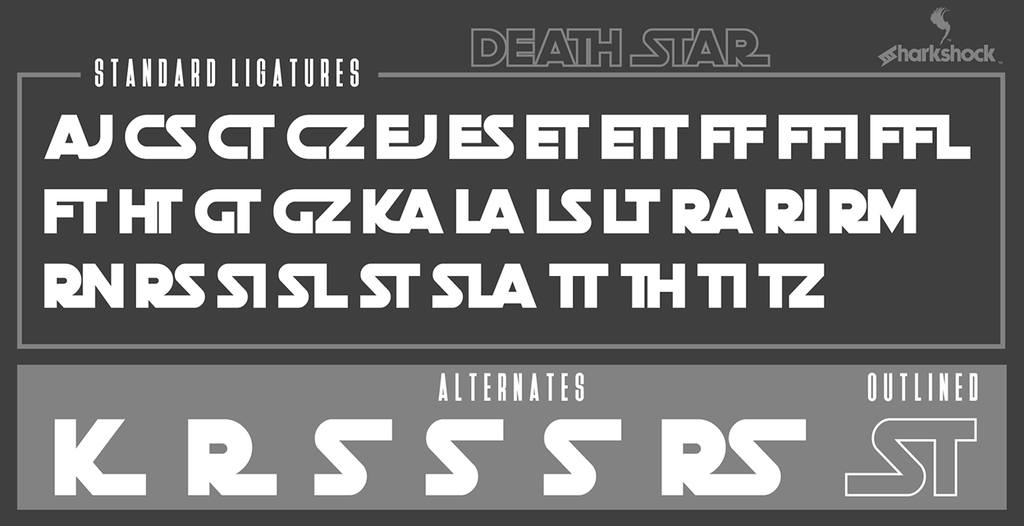
10 ausgezeichnete STEM- und Science-Fonts
Veröffentlicht: 2019-08-09Egal, ob ein Kunde ein retro-futuristisches Design für seine neue Website wünscht, eine Organisation für eine MINT-Veranstaltung in ihrer lokalen Gemeinde wirbt, ein Science-Fiction-Autor ein elegantes Buchcover verlangt oder ein neues Forschungsunternehmen eine hochmoderne Website benötigt, um ihrer Spitzenforschung entsprechen, vermitteln MINT- und Wissenschaftsschriften leicht ein Gefühl von Modernität, klarem Styling und Hightech-Know-how. Mit jedem Eintrag in dieser Liste können Sie das perfekte Design zusammenstellen, in dem sich die Leser wie zu Hause fühlen. Auch wenn sich dieses Zuhause in einer weit, weit entfernten Galaxie befindet.
1. TR2N
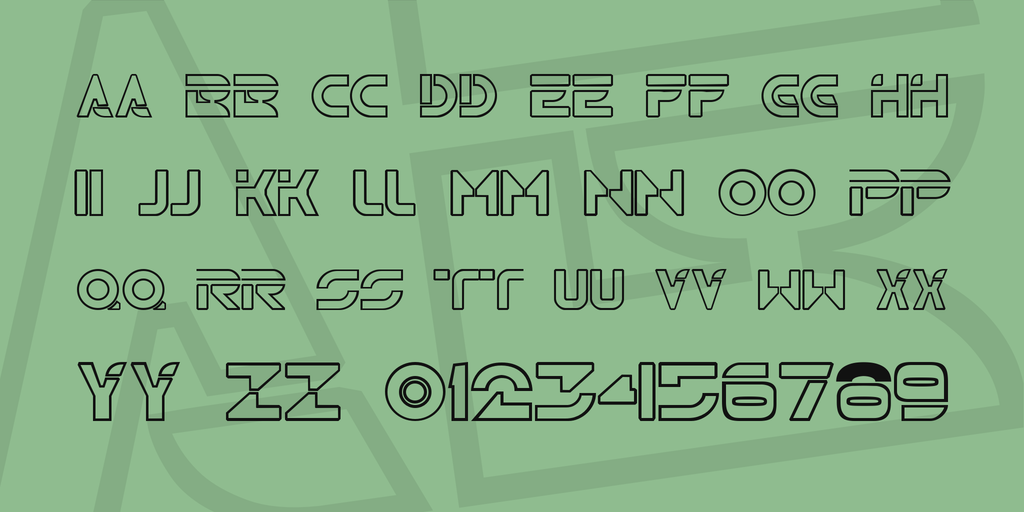
TR2N erinnert an den Disney-Kultklassiker Tron . Diese Schriftart ist eine reine Großbuchstaben-und-Zahlen-Schrift, die nicht für lange Dokumente, sondern für Überschriften und aufmerksamkeitsstarke Designarbeiten entwickelt wurde. Die Schriftart ist gut gemacht und lesbar (für das, was sie ist), ist jedoch stilisiert, sodass Sie dies im Hinterkopf behalten müssen. Wenn es jedoch um Science-Fonts geht (nun, Science-Fiction-Schriften), können Sie nicht viel stärker als TR2N werden. Das Beste daran ist, dass die Schriftart für die kommerzielle Nutzung kostenlos ist, sodass Sie sich in dieser Hinsicht um nichts kümmern müssen.
2. Wissenschaft
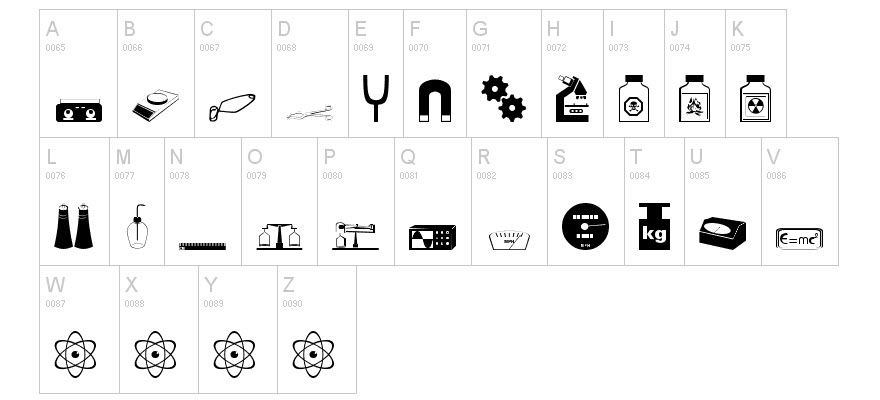
Die passend benannte Science- Schrift ist nicht etwas, mit dem Sie schreiben. Stattdessen handelt es sich um eine Symbolschrift. Jeder Buchstabe auf der Tastatur entspricht einem Symbol eines wissenschaftlichen Symbols, das in so ziemlich jeder Situation nützlich ist, in der Sie eine Wissenschafts- oder STEM-Schriftart benötigen. Die Wissenschaft umfasst Magnete, Zahnräder, gefährliche Chemikalien, Waagen, Mikroskope, Atome und sogar eine E=MC^2-Plakette für ein gutes Maß. (Und noch viel mehr als nur diese.) Mit anderen Worten: Es sind gute Sachen, die Sie herunterladen sollten.
3. GEHACKT
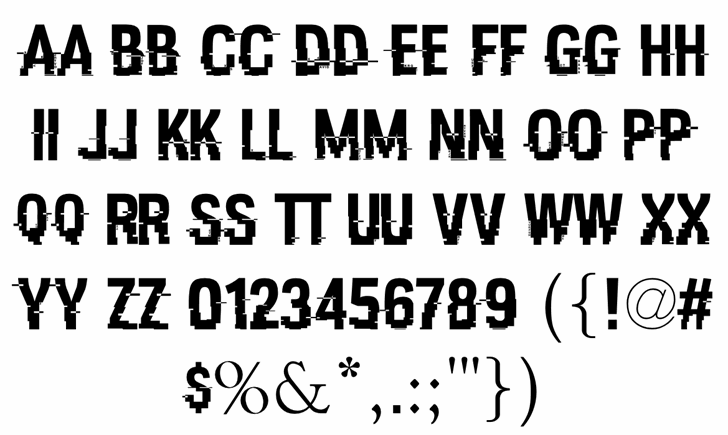
HACKED ist fast die Quintessenz der postmodernen Wissenschaftsschrift. Stellvertretend für den allgegenwärtigen glitzernden Bildschirm, der in vielen Medien auf Hackerangriffe hinweist, ist die Schriftart gut gestaltet und bleibt unabhängig von den Wörtern oder Sätzen immer lesbar. Die Sammlung enthält eine Reihe von Symbolen (und auch Zahlen). Obwohl nur zwei der Symbole das charakteristische Hackey-Glitch-Design haben. Das Hashtag und das Dollarzeichen sind die beiden. Sie können HACKED kostenlos herunterladen. Darüber hinaus können Sie es in kommerziellen Projekten frei verwenden.
4. Primus
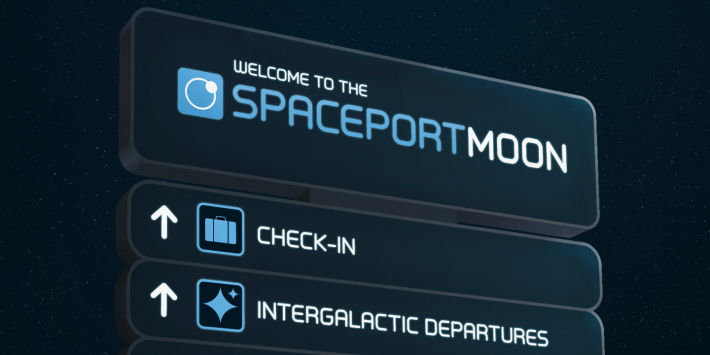
Primus ist eine Schriftart, die in jedem Design oder Dokument zu Hause ist, das eine futuristische Note benötigt. Der Primus eignet sich sowohl für Überschriften als auch für Textkopien, hat einen guten Abstand, abgerundete Kanten an jedem Zeichen und ein Kerning, das Whitespace effektiv nutzt. Es ist perfekt für die Beschilderung in der realen Welt, um MINT-Veranstaltungen oder in Science-Fiction-Medien aller Art zu bewerben. Primus ist sozusagen die perfekte Wissenschaftsschrift, um die saubere und glatte Zukunft zu zeigen, auf die wir alle hoffen.
5. Roddenberry
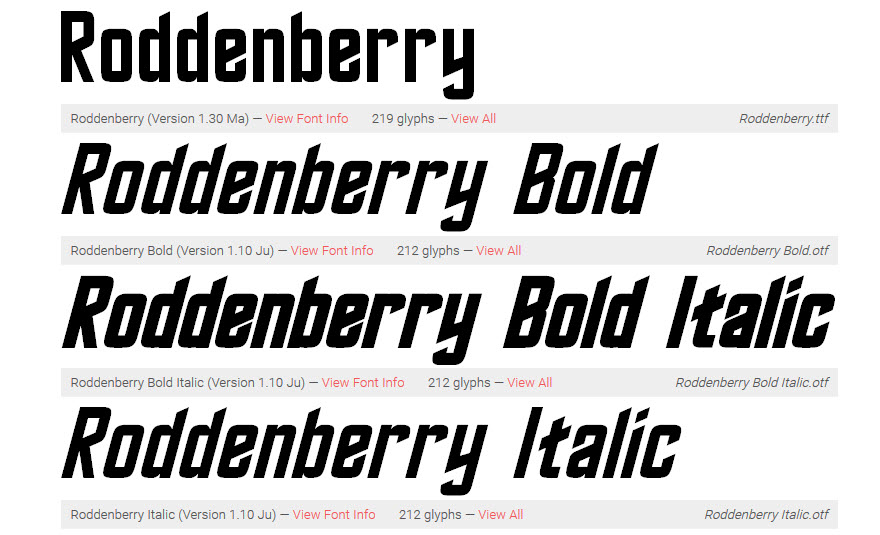
Roddenberry ist der ursprünglichen Star Trek- Titelschrift nachempfunden und verdient einen Platz auf jedem Computer, der sogar darüber nachdenkt, eine STEM-bezogene Schriftart zu verwenden.
6. Weltraumschrott: XL
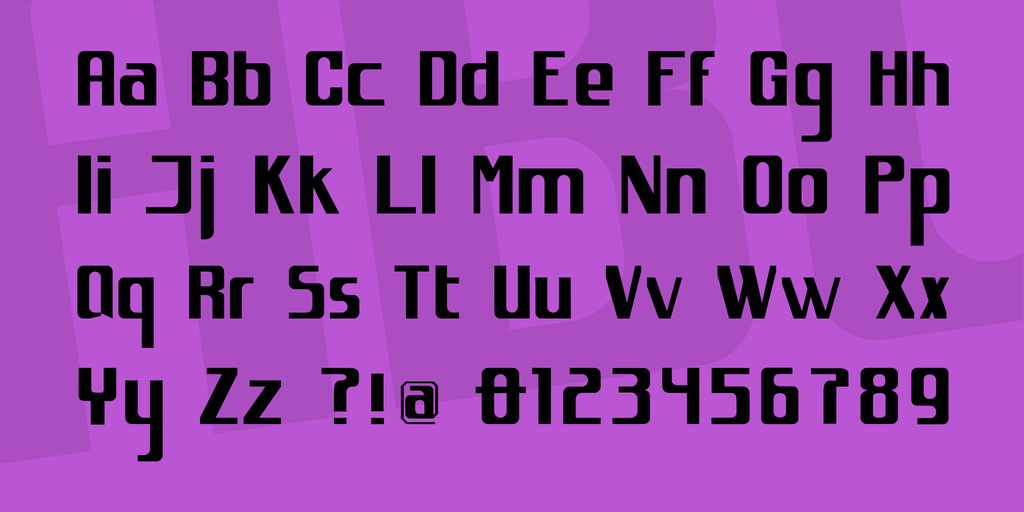
Wenn Sie eine Schriftart benötigen, die gleichzeitig futuristisch und leicht vintage aussieht, ist spacejunk:XL eine gute Option. Eine einfache Schriftart, spacejunk:XL, ist keine Monospace-Schrift, sodass Sie damit dynamische Anzeigen erstellen können, die die Aufmerksamkeit der Leser auf sich ziehen, ohne tief in die Feinabstimmung von Photoshop oder Illustrator einsteigen zu müssen.
7. BP-Moleküle
Sie können nicht viel wissenschaftlicher als BP-Moleküle werden . Wer sich die Schrift anschaut, erkennt sofort die ihm vermittelten MINT-Obertöne. Die Sammlung enthält keine Glyphen in Kleinbuchstaben, aber wenn Sie eine Schriftart verwenden, die die Molekülstruktur nachahmt (und stilisiert), sind Sie möglicherweise nicht so besorgt. Sie können die Schriftart dank der Creative Commons-Lizenzierung in kommerziellen Projekten verwenden und enthalten tatsächlich griechische und koptische Glyphen, die Ihnen viel mehr Nutzen aus der Schriftart bieten. Sie möchten diese 41 Glyphen auf jeden Fall in Ihrer Bibliothek haben.
8. Todesstern
Vor langer Zeit, in einer weit, weit entfernten Galaxie…
Entschuldigung, wir konnten nicht widerstehen. Wenn Sie jedoch möchten, dass eine Wissenschaftsschrift bei Ihrem Publikum die Star Wars- Nostalgie hervorruft, ist Death Star der richtige Weg. Eines der interessantesten Features von Death Star sind die enthaltenen Ligatur-Charaktere, die den Vintage-Filmplakaten ihr ikonisches Gefühl verleihen. Die Schriftart kann kostenlos heruntergeladen werden; Mit einer Spende von 15 USD (oder dem Kauf einer kommerziellen Lizenz) erhalten Sie jedoch nicht nur Zugriff auf die reguläre Version (blockiert), sondern auch auf das Gliederungsformular. Das ist kein schlechter Preis für zwei separate Schriftarten, die jedes Design, das sofort erkennbar sein soll, wirklich beleben können.
9. Computer 7
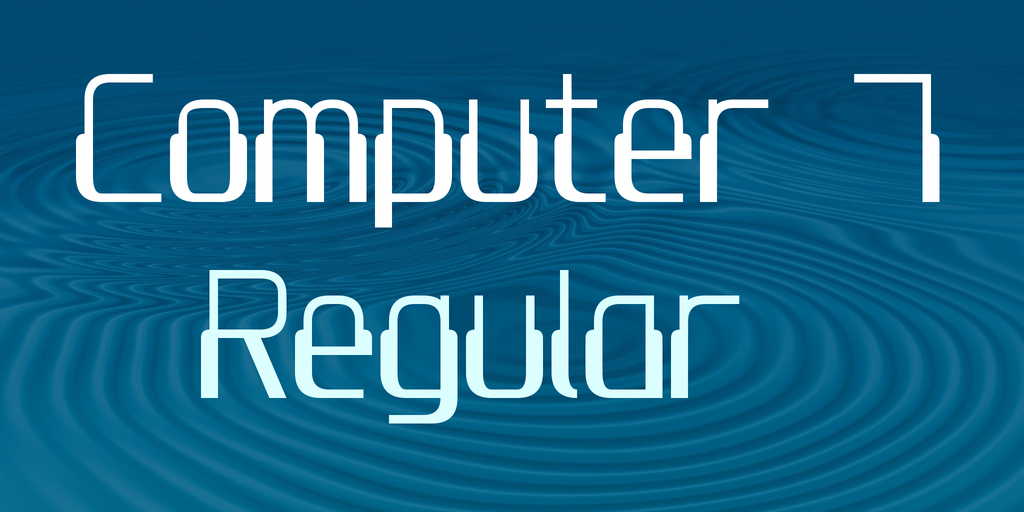
Computer in den 1980er Jahren hatten ein einzigartiges Design für ihre Schriftarten. Es wurde in späteren Generationen von Computern nicht fortgesetzt (zumindest standardmäßig), aber Sie können die Erinnerungen des Apple IIe und des Commodore 64 mit Computer 7 erneut aufrufen. Ursprünglich in Pixeln angezeigt, bietet Computer 7 viel mehr Vielseitigkeit. Diese Schriftart eignet sich hervorragend zum Erstellen von Überschriften und großen Textanzeigen, die an Retro-Computing erinnern müssen, aber aufgrund ihrer Ursprünge in der tatsächlichen Computernutzung für den täglichen Gebrauch können Sie darin sehr leicht lesbare Langformdokumente erstellen. Wir empfehlen jedoch, dass Sie sich für mehr als nur Textblöcke an modernere Schriftarten halten. Computer 7 kann kostenlos für den Heimgebrauch heruntergeladen werden, Sie müssen jedoch eine Lizenz für 24,95 USD erwerben, wenn Sie ihn kommerziell verwenden möchten. Es kommt auch mit Groß- und Kleinbuchstaben, Zahlen und Symbolen.